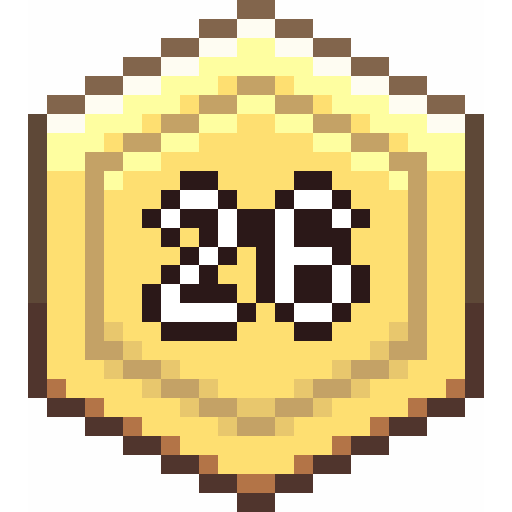
Wynncraft Hud Font More Readable
Ресурспак Wynncraft Hud Font More Readable делает шрифт интерфейса более читаемым. Больше не надо щуриться, чтобы разобрать 2 и 6 в оригинальном HUD сервера Wynncraft.
Если вы играли на сервере Wynncraft в Майнкрафт, то наверняка сталкивались с проблемой: цифры 2 и 6 в оригинальном шрифте HUD сливаются в одну нечитаемую кашу. Особенно в суровых битвах, когда каждая секунда на счету, разбирать эти символы - то еще испытание для глаз.
Wynncraft Hud Font More Readable - это простой, но крайне полезный ресурспак, который решает именно эту проблему. Автор (Focal) просто взял и заменил шрифт на более разборчивый. Никаких лишних наворотов, только суть: 2 и 6 теперь четко различимы, и HUD становится по-настоящему читабельным.
Как это выглядит
Правда, стоит учитывать: ресурспак меняет только шрифт HUD, но не трогает остальные элементы интерфейса самого сервера. Так что атмосфера Wynncraft останется прежней, просто станет удобнее.